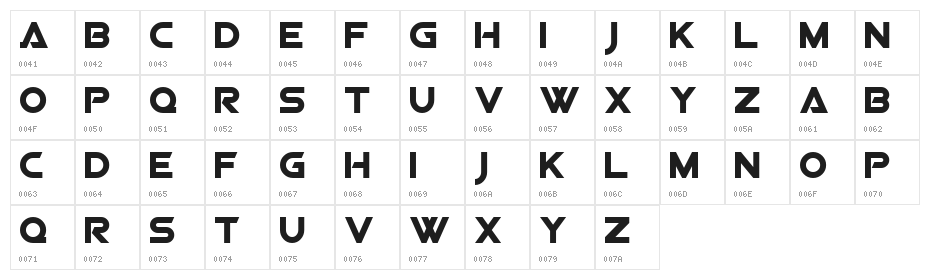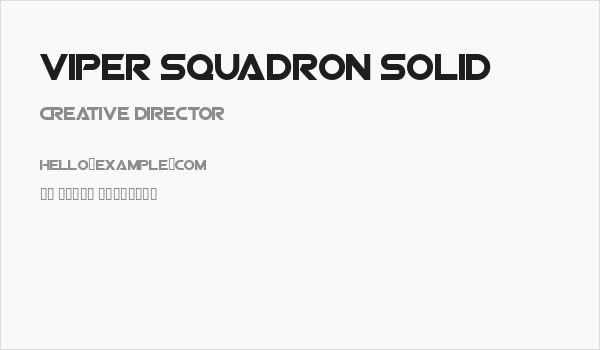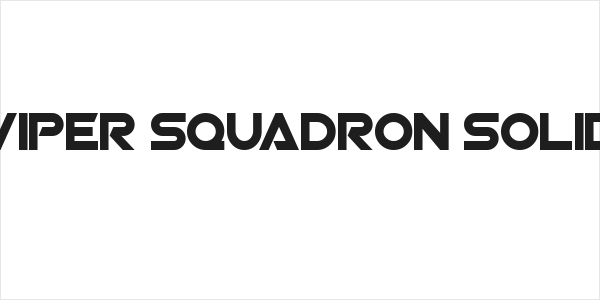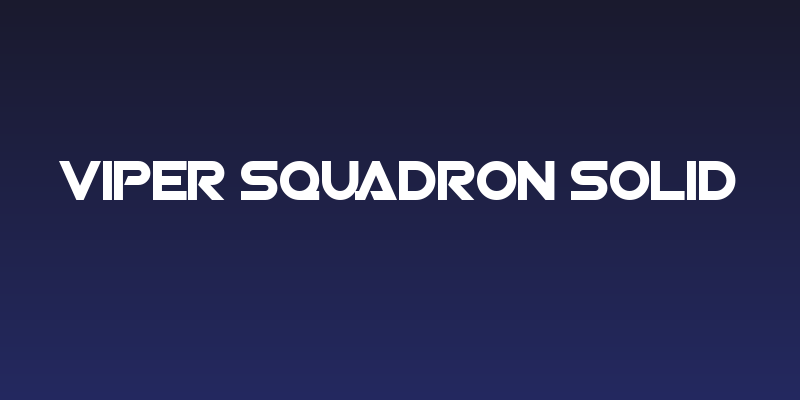
Viper Squadron Solid Font
| Vorgeschlagene Projekte | Ideal for sci-fi movie posters, video game titles, tech company logos, and futuristic branding. |